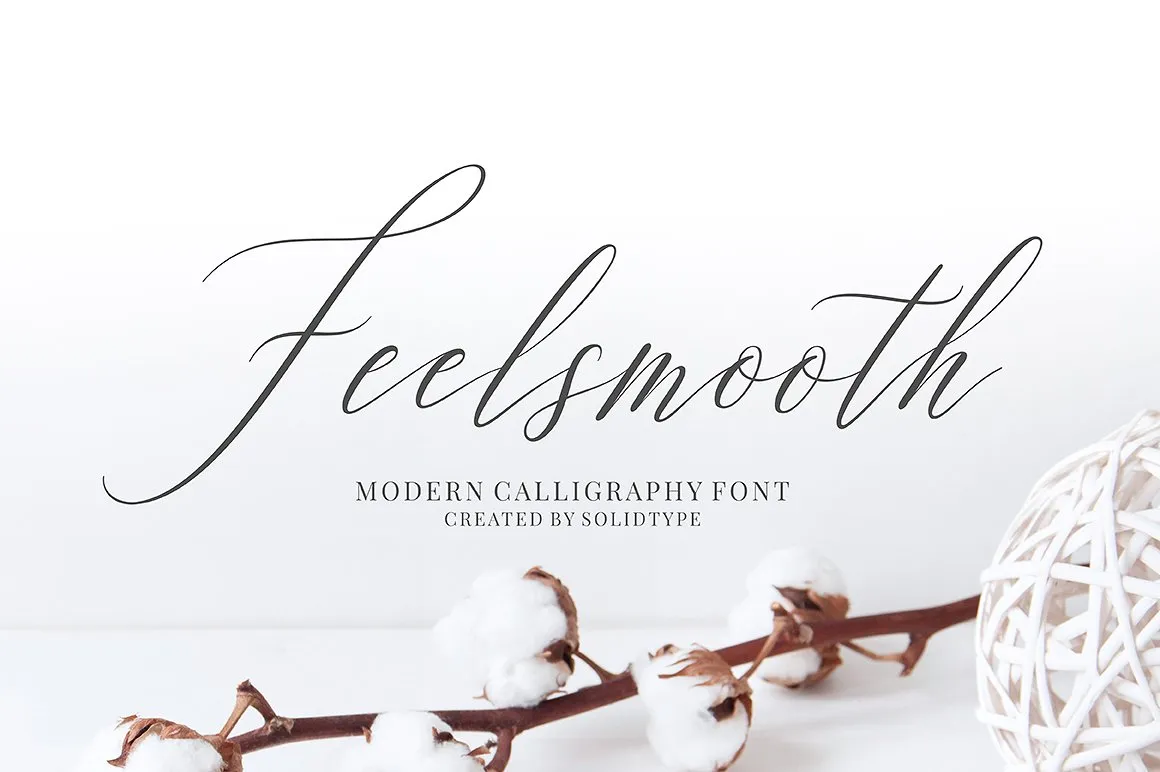
A Feelsmooth Script Font é uma nova adição à categoria dos tipos de letra script moderna, ideal para projetos variados que valorizam um toque elegante e sofisticado. Através dessa fonte de tipo, você pode criar gráficos que se destacam pelo seu design moderno e delicado, com linhas suaves e um rastro de tração variável. Feelsmooth Script destaca-se por oferecer 350+ caracteres gílios e até 167 alternativas para os caracteres, o que aumenta ainda mais a sua versatilidade. Com todas as letras minúsculas incluídas em alternativas com esquives ao início e fim, essa fonte proporciona resultados incrivelmente belos e fáceis de usar. Perfeita tanto para criação de logotipos quanto para mensagens pessoais ou convites, a Feelsmooth Script é uma escolha ideal para quem busca um toque sofisticado em seus projetos gráficos. Seja para uma simples carta ou para imprimir material corporativo, essa fonte oferece um toque suave e elegante que certamente se adequará perfeitamente ao seu trabalho.